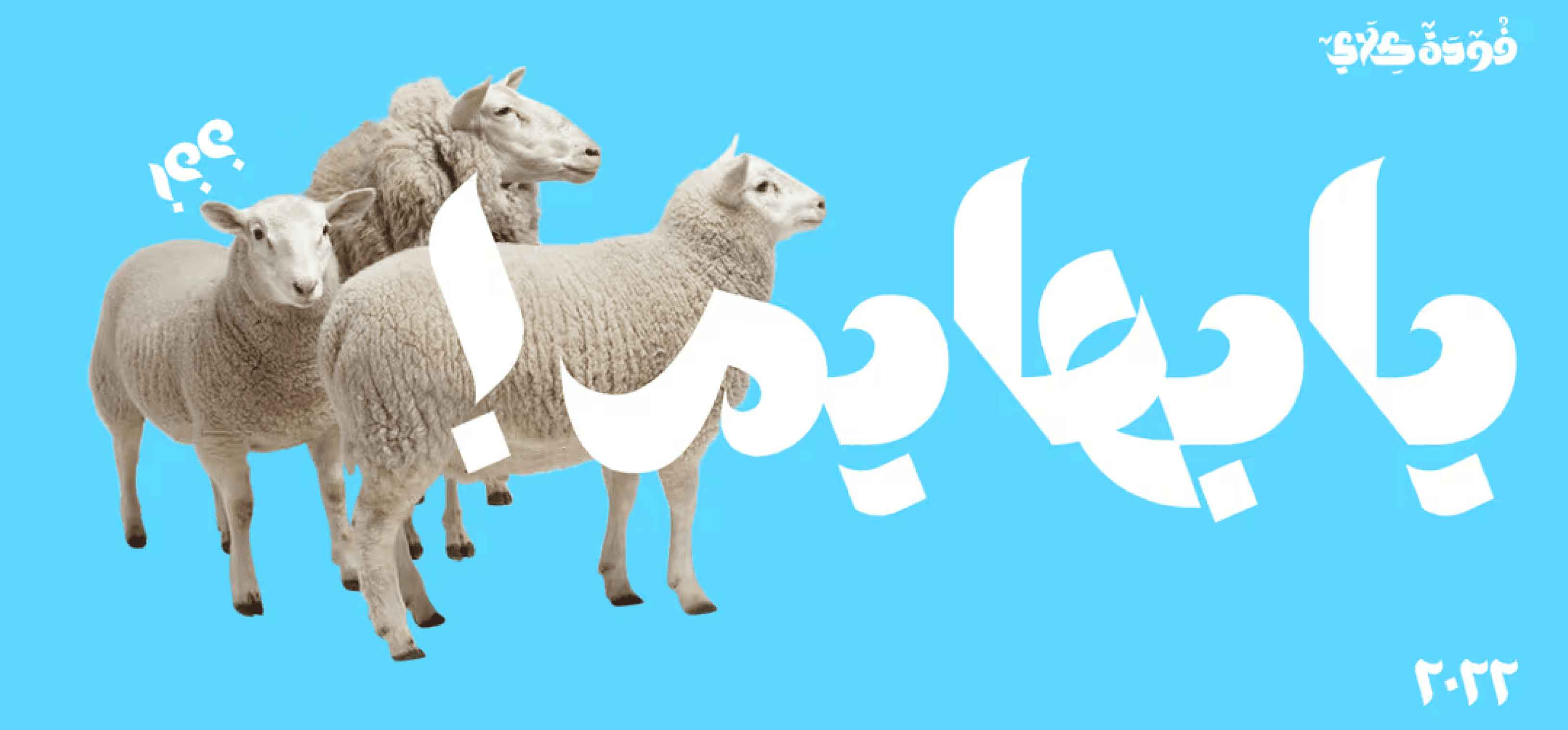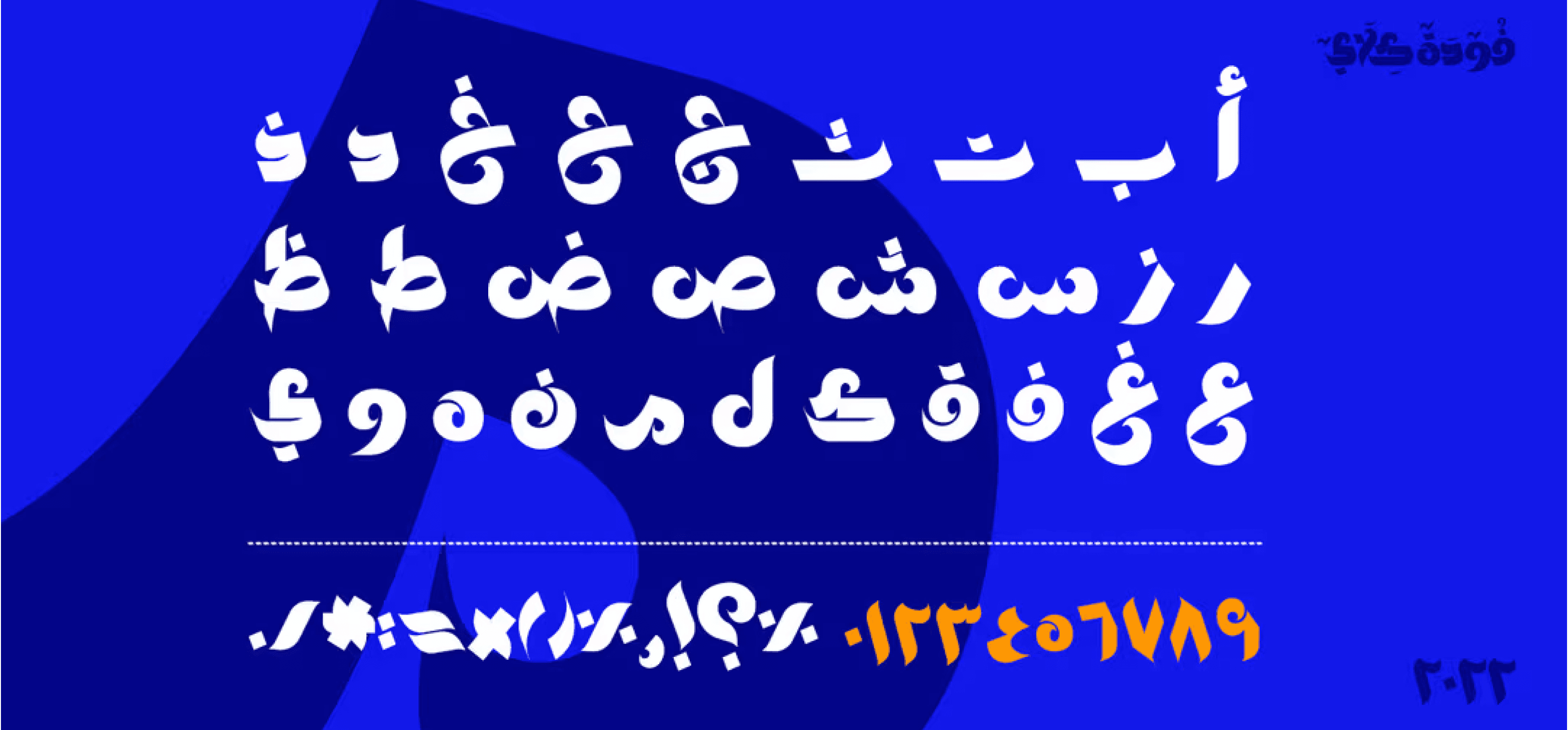
هو خط عربي عصري يتميز باحتوائه على عدد كبير من الحروف والتراكيب (Ligatures)، مما يمنحه طابعًا بصريًا مميزًا ومتجددًا.
يُعد Foda Klay خيارًا مثاليًا لتصميم الشعارات، الهوية البصرية، الملابس، التغليف، العناوين، والإعلانات.